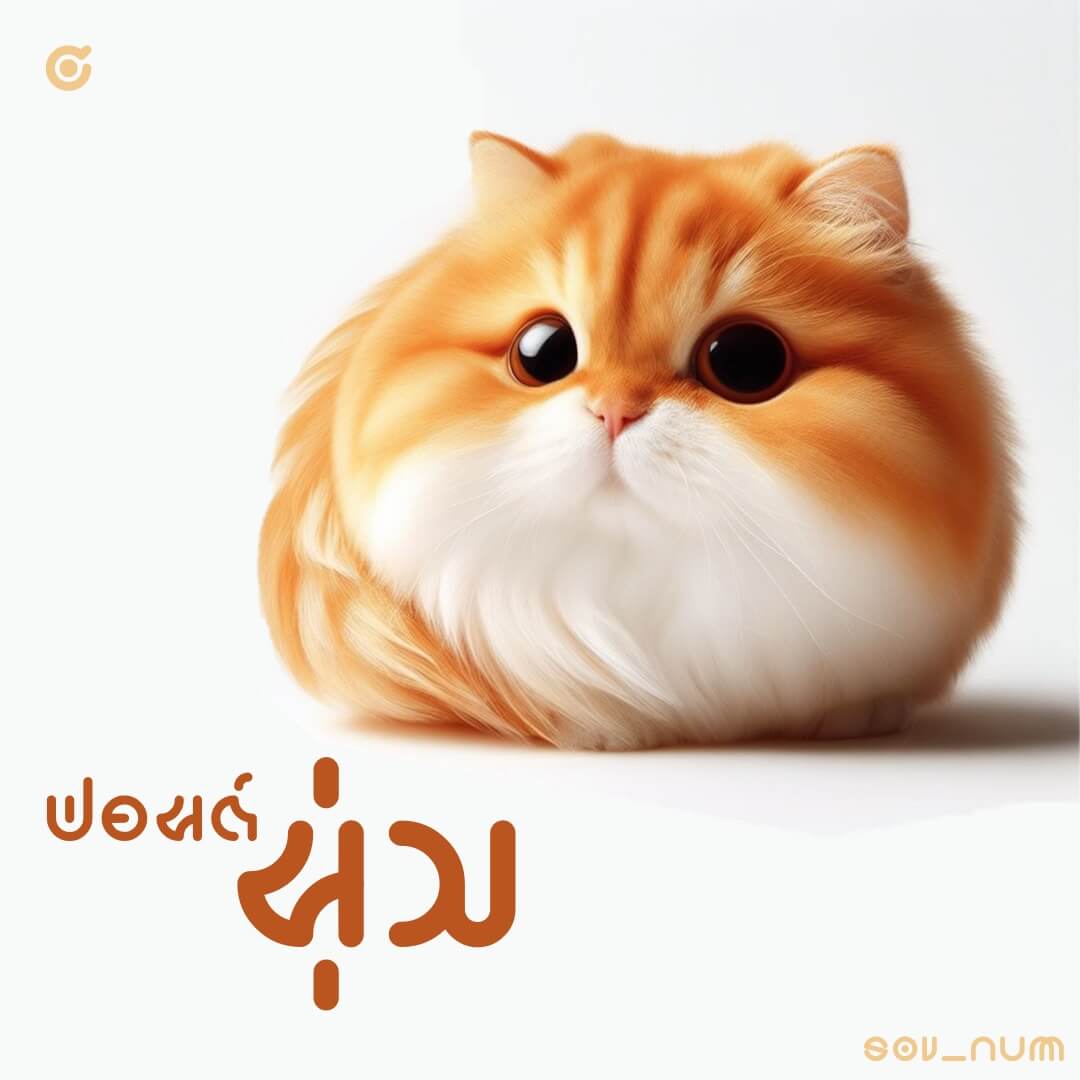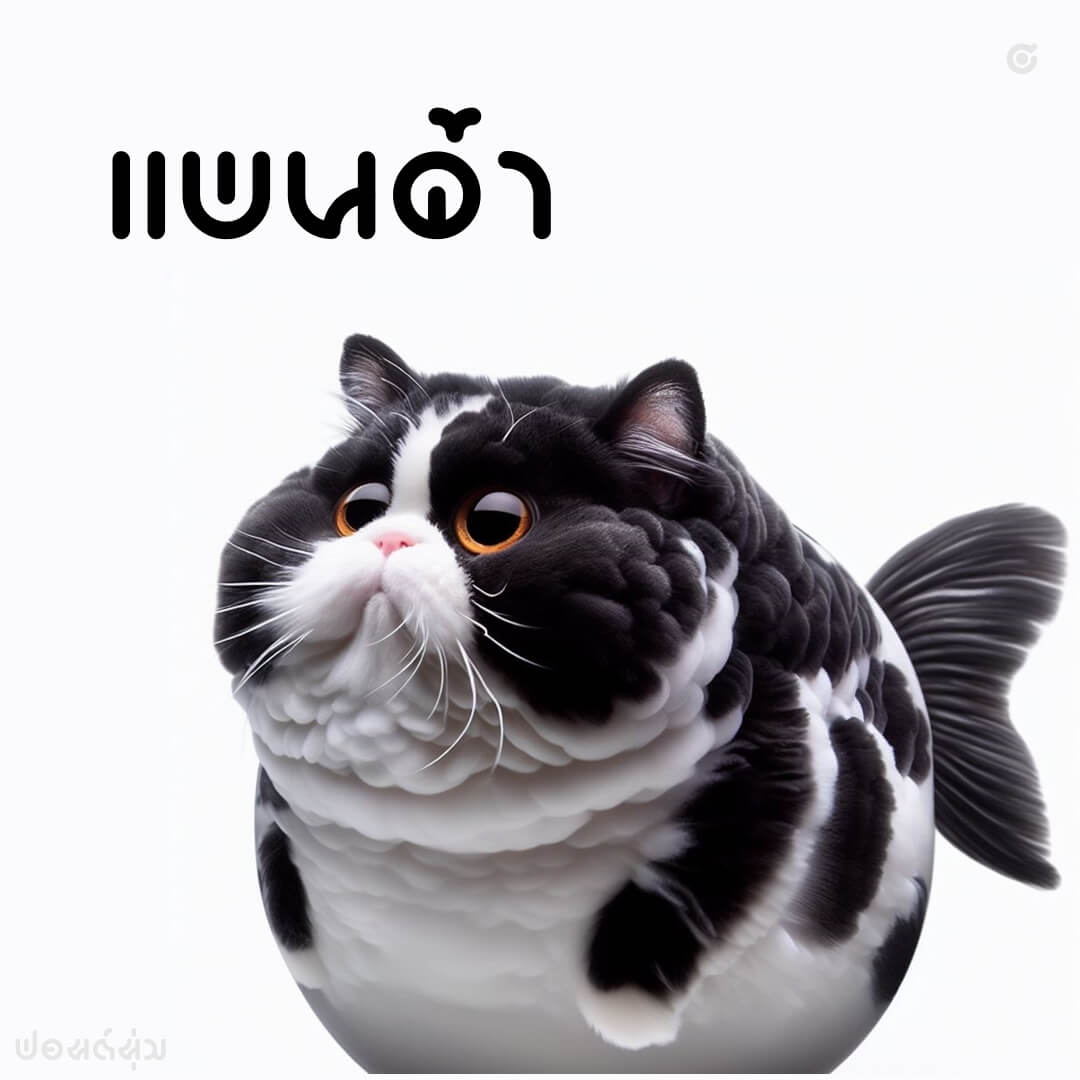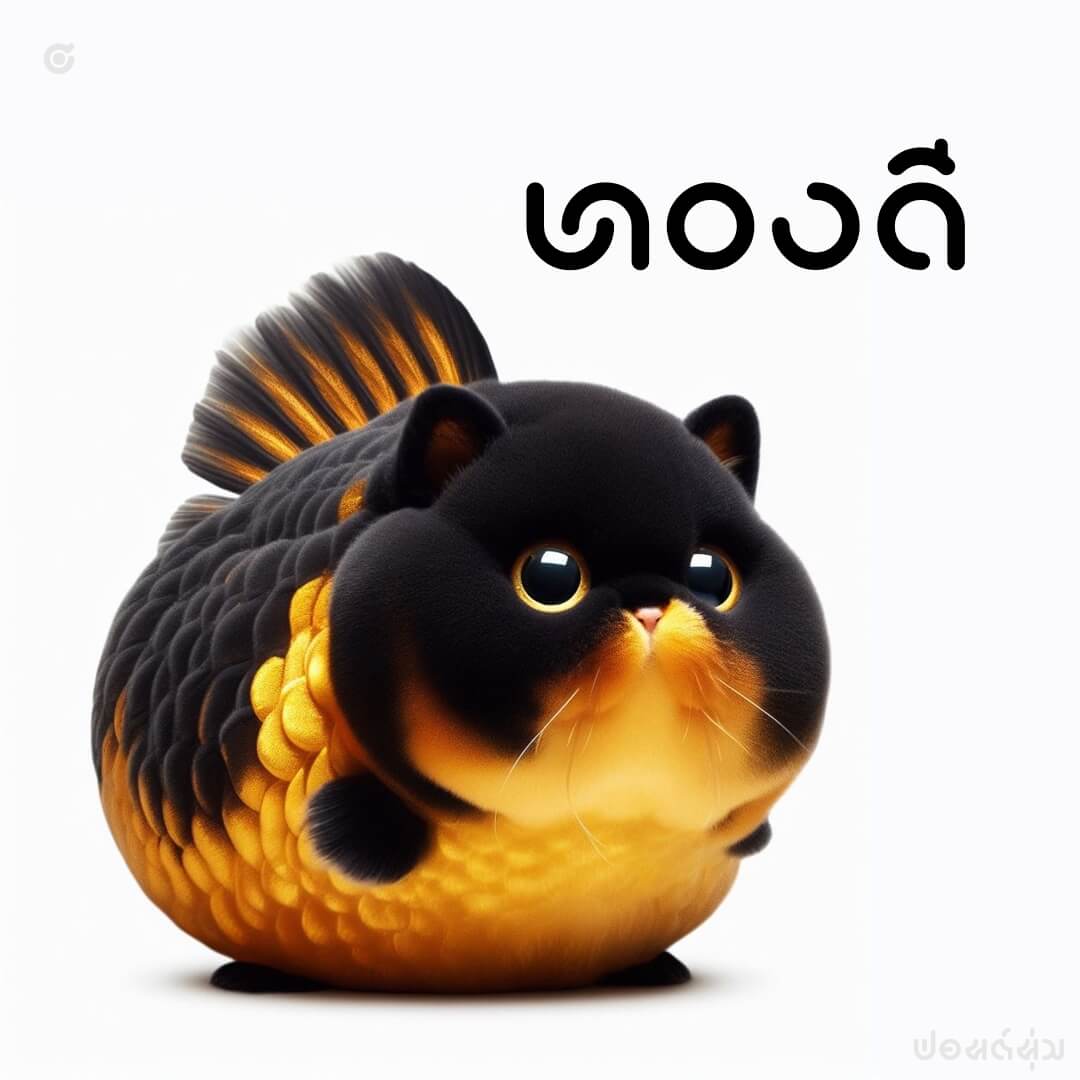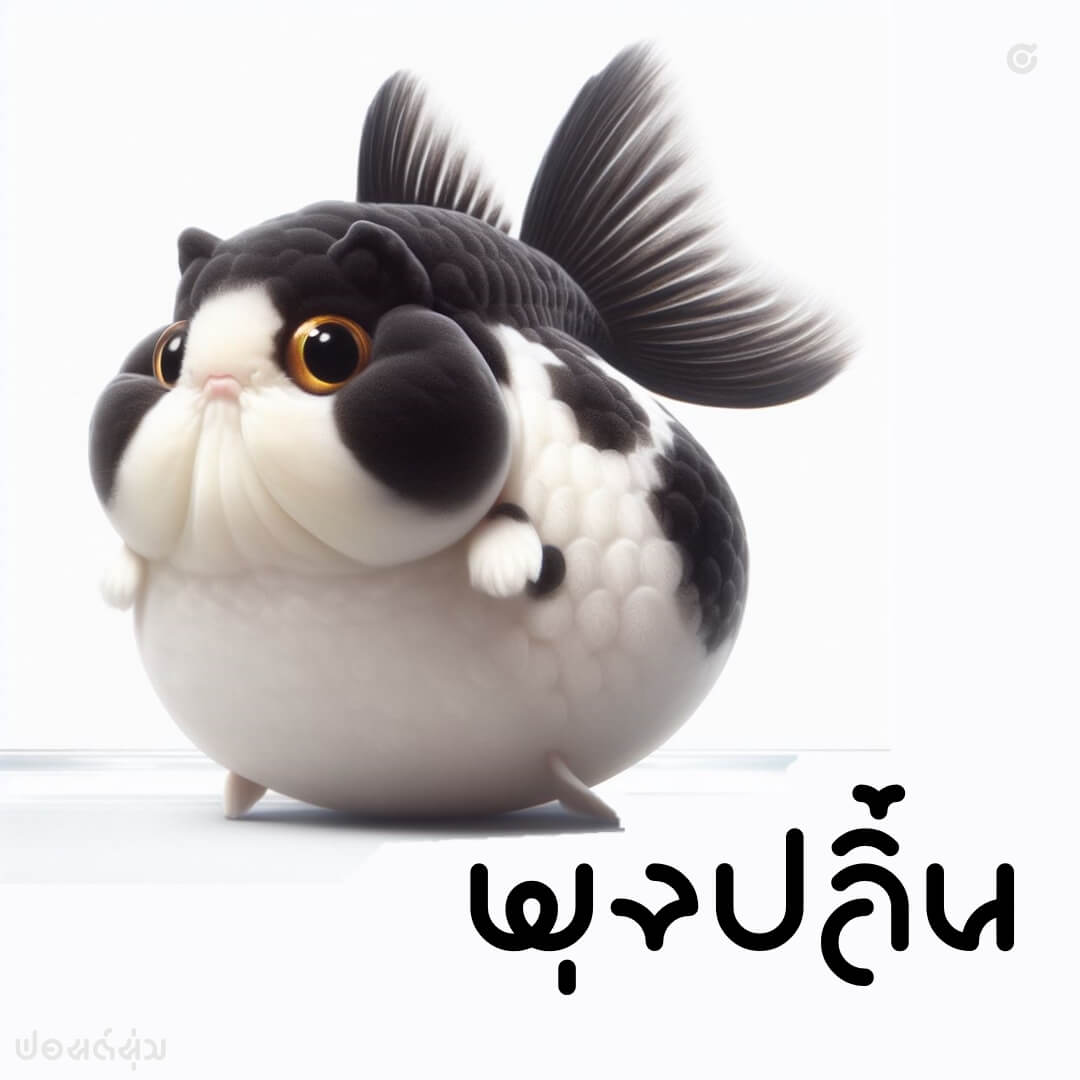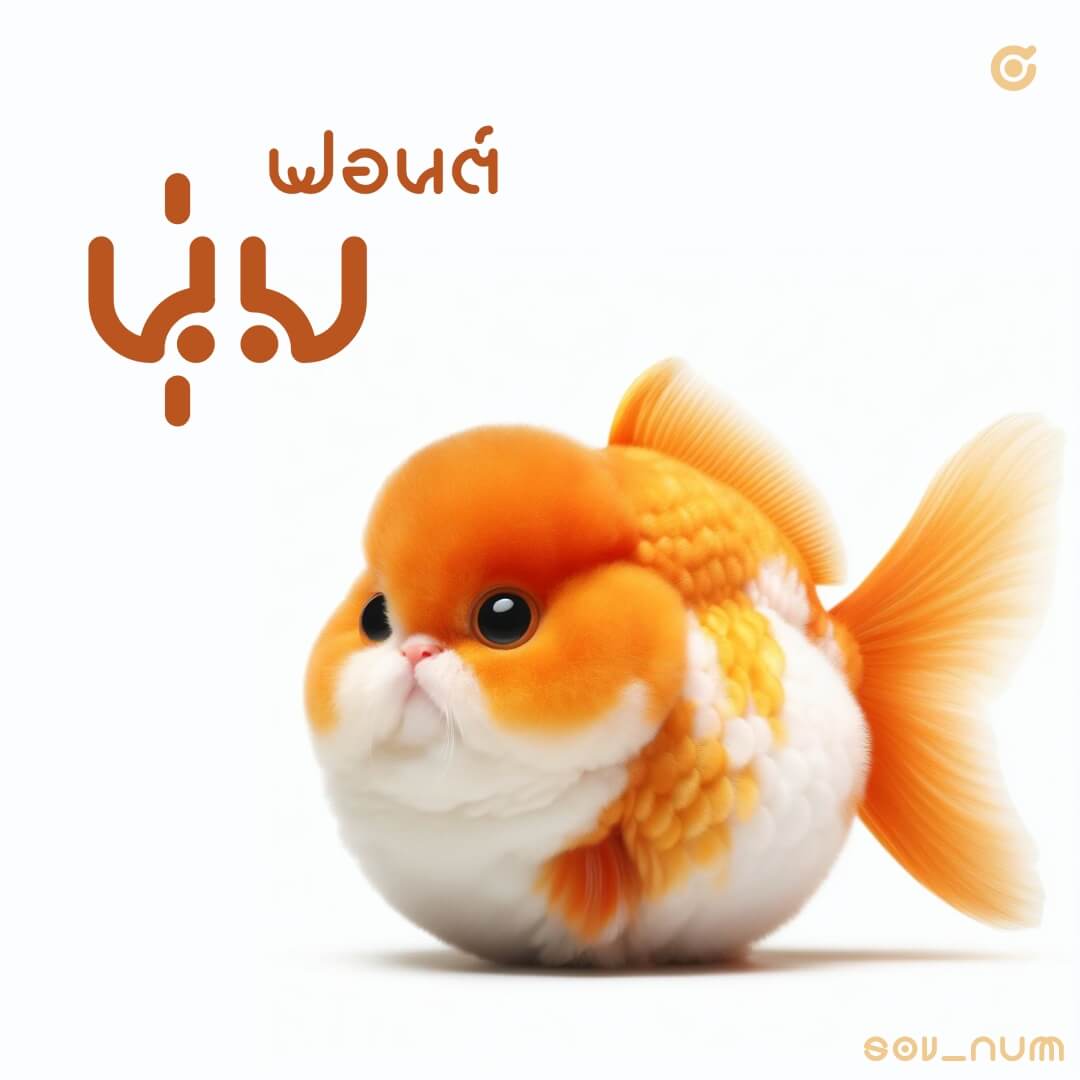
นุ่ม (SOV_num)
futuristic logo กลม โค้ง
ฟอนต์นุ่ม – logo font หน้าตาแปลกๆ ตั้งต้นที่เส้นวงกลม แล้วแยกชิ้นส่วนพลิกๆพลิกมา ถ้าอ่านยากไปลองใช้ตัวพิเศษเพิ่มอีก 2 แบบที่เตรียมไว้ (ใช้ ฯฯ นำหน้า)
เบื้องหลังการออกแบบ : ฟอนต์ นุ่ม